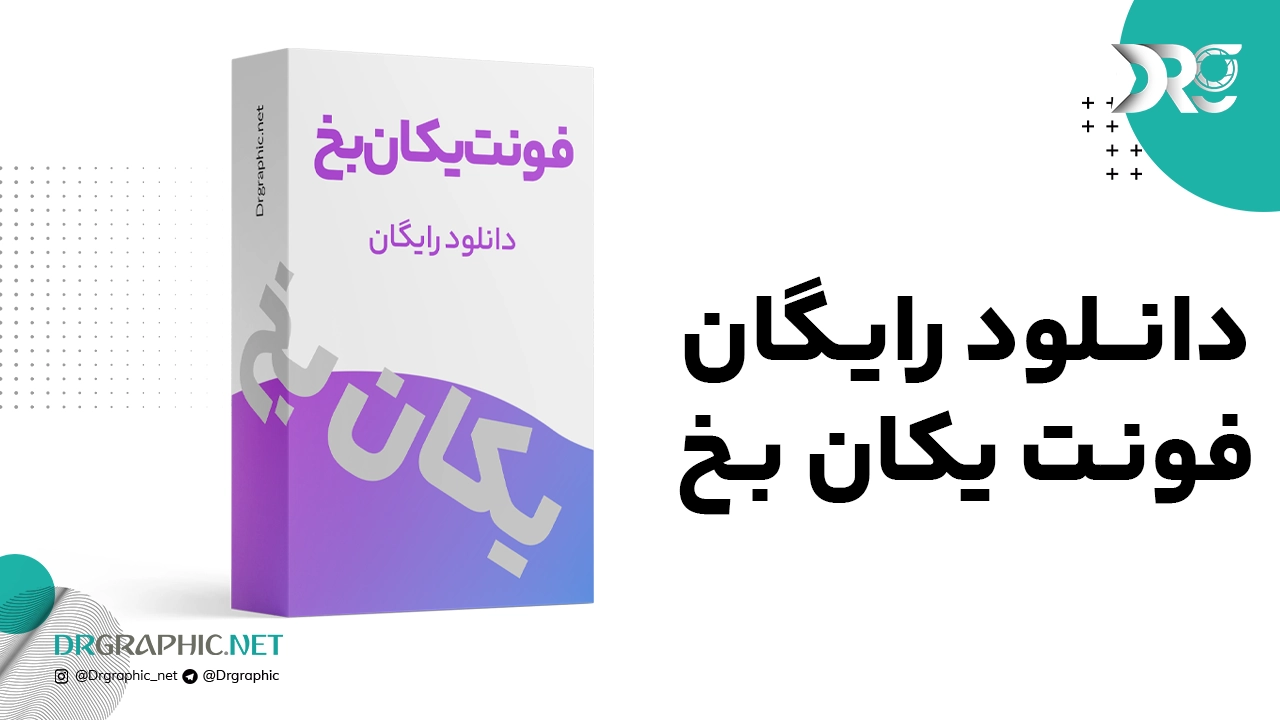
دانلود رایگان فونت یکان بخ
فونت یکان یکی از قدیمی ترین فونت های گرافیکی ایرانی می باشد که در سیستم های ما فارسی زبانان استفاده شده است. این فونت با تمام سادگی ای که در خود دارد توانسته جلوه ی بسیار زیبایی به متن های فارسی ارائه کند.
امروزه پایه بسیاری از فونت های وب فارسی، لوگوتراپی یکان می باشد. فونت رایگان یکان در ابتدا توسط مديریت هنرى و توليد زنده ياد مسعود سپهر و طراح خانم سیما مشتاقی طراحی شده بود و به مرور زمان توسط افراد مختلف توسعه داده شده است. متاسفانه به دلیل نبود مرجعی واحد برای این فونت زیبای فارسی نسخه های مختلف آن را با نام های مختلف توسعه داده اند.
از مهمترین ویژگی ها و مزیت های این فونت خوانایی بسیار بالای آن است که باعث شده است که بیشتر مدیران سایت ها و کسب و کارهای آنلاین از این فونت در وب سایت خود استفاده کنند، از زمان انتشار این فونت، بسیاری از سایت های حتی فونت ایران سنس خود را به یکان بخ تغییر دادند، در ادامه بیشتر با مزیت های این فونت آشنا خواهید شد.